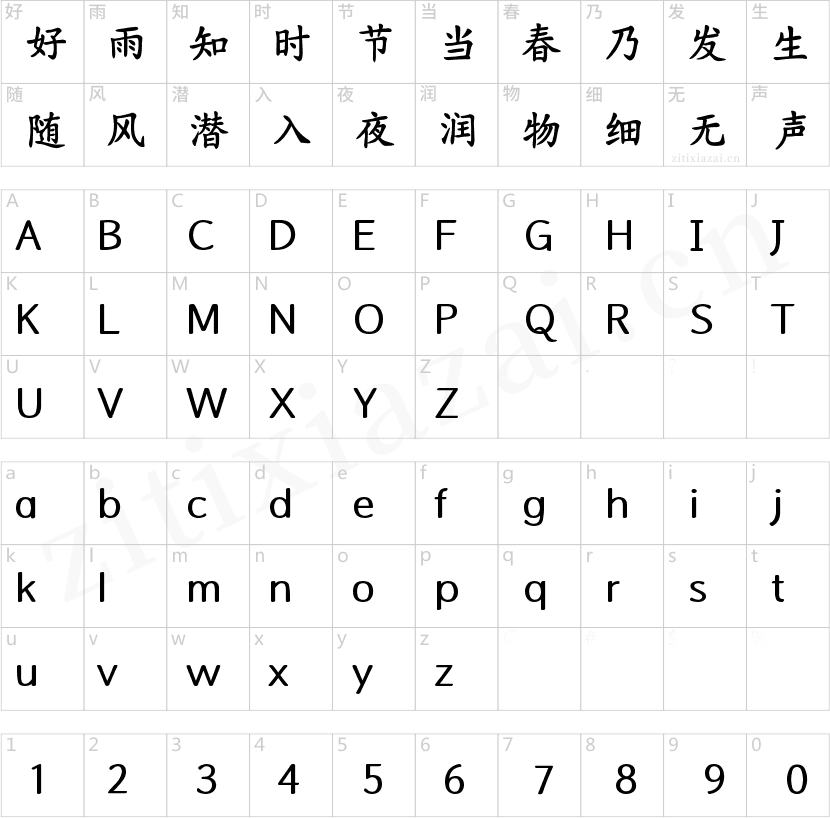
Aa清风楷书超大字库
Aa清风楷书超大字库字体
Aa清风楷书超大字库是一款非常具有艺术性的字体,它的设计灵感来源于对古典艺术的研究,同时又融入了现代字体设计的元素。字形优美,笔画粗细变化自然,给人以大气、典雅的感觉。Aa清风楷书超大字库是一款既传统又现代的字体,它的设计充满艺术感,美观大方,实用性也非常强。无论是对于设计师还是对于普通读者来说,都是一种非常不错的字体选择。Aa清风楷书超大字库适合用于具有艺术感的场合,比如海报、宣传单张、书籍封面等。由于其字形流畅且具有动态感,也适合用于大量的文本排版,如报纸、杂志等。